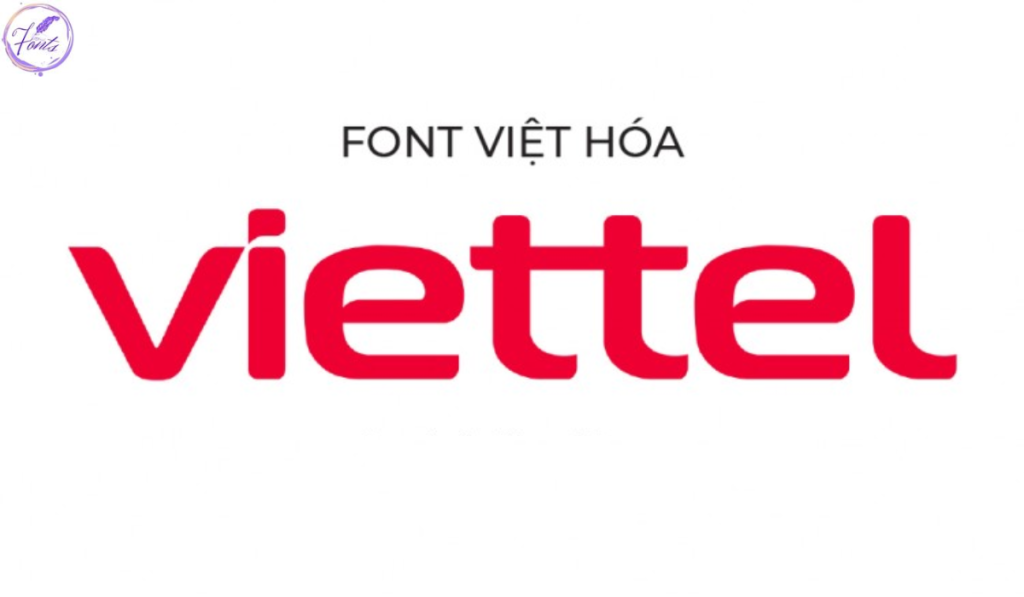
Font chữ viettel việt hóa – Font FS PF BeauSans Pro Việt hóa
Tác giả: Viettel Font Studio
Bộ Font: Viettel Font
Phân loại: Cá tính, hiện đại
Kiểu chữ: Kiểu chữ không chân
Độ dày: Regular, Bold
Font chữ Viettel được phát triển bởi đội ngũ thiết kế của Viettel vào năm 2020, là một trong những phông chữ hiện đại dành riêng cho thương hiệu này. Font này bao gồm các đặc tính kỹ thuật cao, nhằm mục đích tăng cường độ rõ nét và khả năng đọc trên mọi nền tảng số. Với sự phù hợp hoàn hảo cho branding và marketing, font Viettel không chỉ hữu ích cho công ty mà còn dành cho cả cộng đồng sáng tạo, những người tìm kiếm một phong cách đặc trưng và mới mẻ.